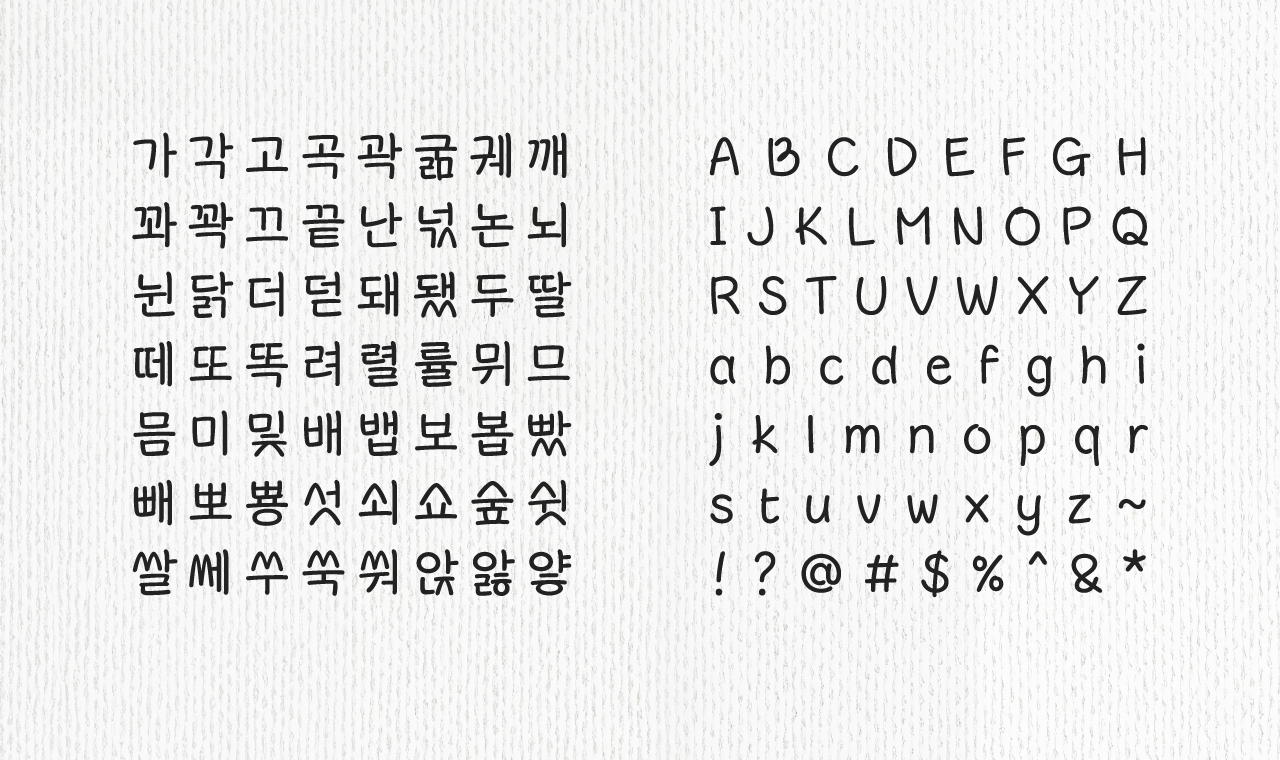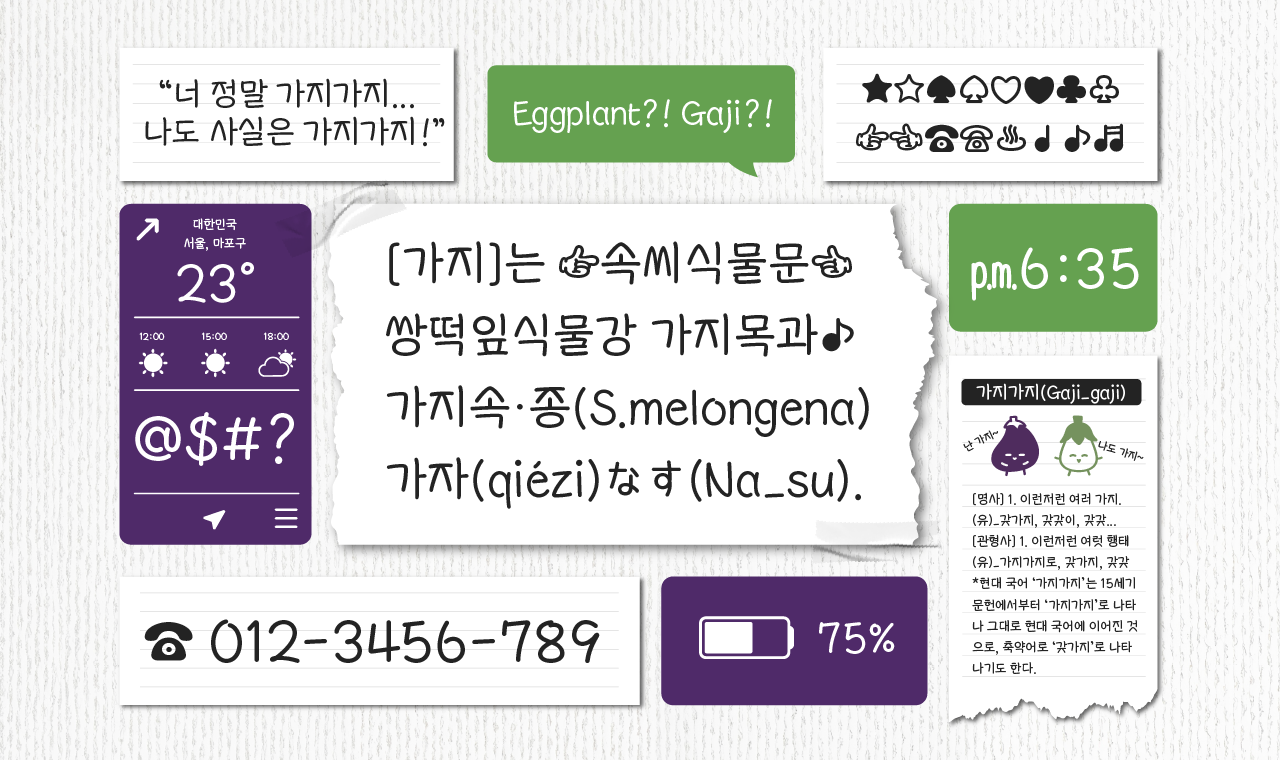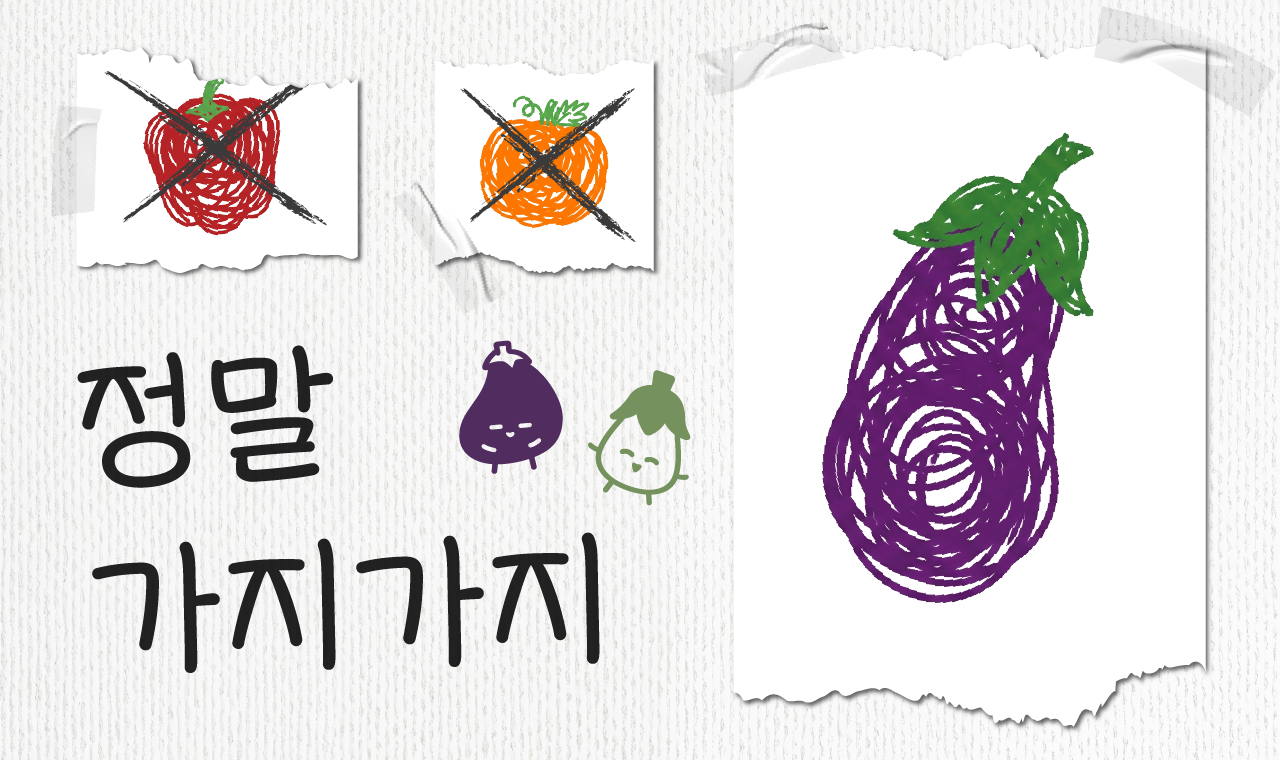
정말가지가지
Yoon 정말가지가지
정말가지가지는 정말 ‘가지가지’하는 ‘가지’를 모티브로 만든 폰트입니다. 귀여운 가지는 맛있고 건강한 채소지만, 가끔 너무하다시피할 정도로 ‘가지가지’하는 경향이 있습니다. ;), ;>의 히든딩벳으로 정말 ‘가지가지’하는 ‘가지’를 입력해보세요.